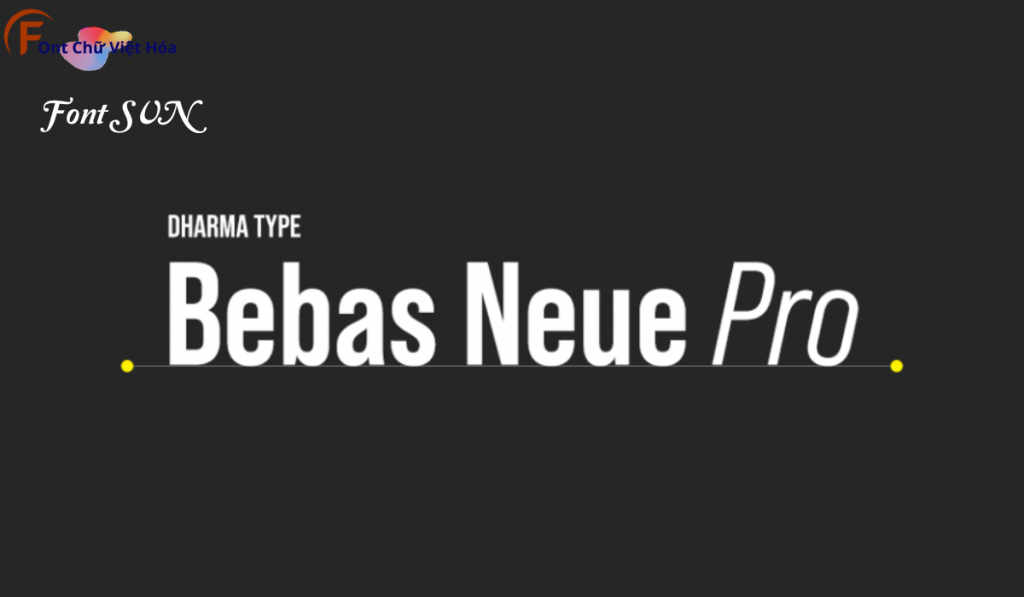
Font Việt Hoá SVN-Bebas Neue
Độ dày: Mỏng, Thường, Đậm
Font Việt Hoá SVN-Bebas Neue là một font chữ không chân hiện đại, thuộc bộ font SVN. Được thiết kế với mục tiêu mang lại sự tinh tế và thanh lịch, font này phù hợp cho các dự án thiết kế như website, tài liệu, và bao bì sản phẩm. Với các nét chữ rõ ràng và độ dày đều đặn, Font Việt Hoá SVN-Bebas Neue không chỉ dễ đọc mà còn tạo cảm giác chuyên nghiệp. Việc Việt hóa font giúp người dùng dễ dàng sử dụng trong các thiết kế tiếng Việt, mang lại sự tiện lợi và thẩm mỹ cao.